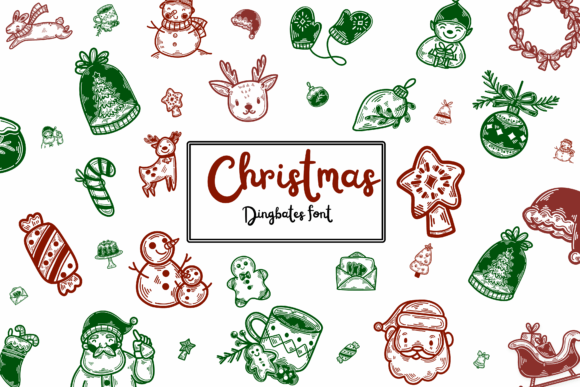
Christmas
Die richtigen Designelemente zu finden, kann eine Herausforderung sein, aber Christmas bietet eine außergewöhnliche Sammlung, die Ihre Arbeit sofort aufwertet.
Egal, ob Sie POD-Produkte (Print on Demand), Hochzeitseinladungen oder Social-Media-Grafiken erstellen, Christmas ist die ideale Wahl.